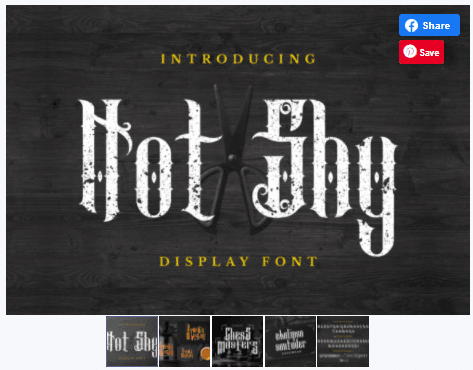
Not Shy Font
Not Shy — это готический стиль и отличный шрифт blackletter. Он невероятно хорошо смотрится на этикетках, брендинге, письмах или приглашениях. С уверенностью добавляйте его в свои любимые творения и позвольте себе удивиться полученному результату.